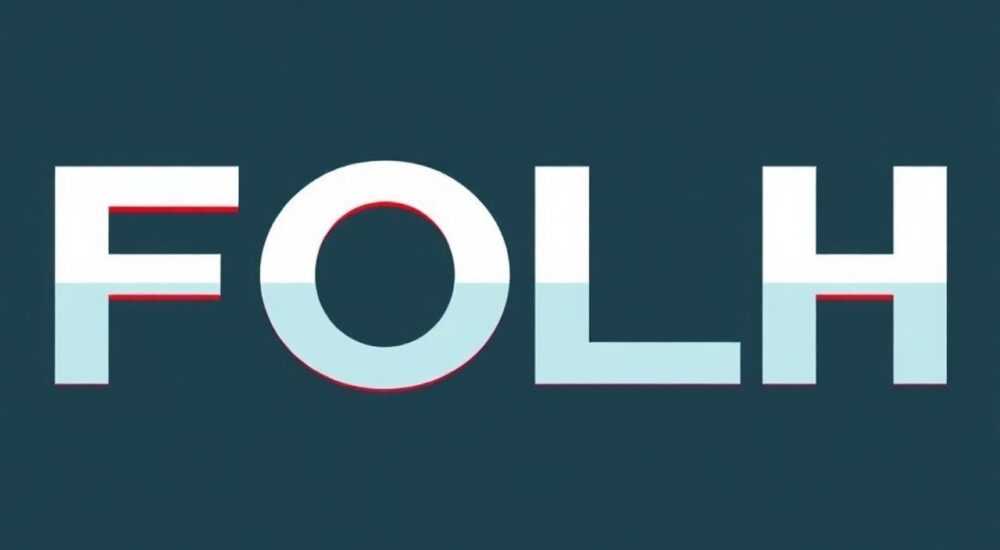
Как сделать толстый шрифт в фотошопе
В графическом дизайне толщина шрифта — один из ключевых инструментов визуальной иерархии. Она помогает выделить заголовки, усилить эмоциональное воздействие текста и сделать макет более читаемым. Однако не всегда в наличии есть нужный жирный начертание шрифта, особенно если используется кастомный или редкий гарнитур. В таких случаях дизайнеры часто сталкиваются с вопросом: как сделать толстый шрифт в Фотошопе? Ответ лежит не только в стандартных настройках стиля текста, но и в продвинутых методах обводки, масштабирования и векторного редактирования.
Почему важна толщина шрифта в дизайне
Толщина шрифта (или его «вес») — это характеристика, определяющая насыщенность линий символа. По международной классификации CSS она варьируется от 100 (тонкий) до 900 (черный). В дизайне вес шрифта влияет на восприятие информации: чем он выше, тем агрессивнее и доминантнее выглядит текст. Это делает жирные шрифты идеальными для заголовков, рекламных баннеров и call-to-action элементов.
Исследования Nielsen Norman Group показывают, что пользователи сканируют веб-страницы по F-образной модели. Жирные слова попадают в фокус внимания в 3.5 раза чаще, чем обычный текст. Это подтверждает важность правильного использования толщины шрифта для повышения конверсии и читаемости.
Однако не все шрифты имеют встроенное жирное начертание. Особенно это касается кастомных шрифтов, рукописных или декоративных гарнитур. В таких случаях дизайнер должен самостоятельно создать эффект утолщения, не нарушая пропорций и качества текста.
Как использовать встроенные жирные начертания
Перед тем как прибегать к хитростям, проверьте, доступно ли у вас настоящее жирное начертание выбранного шрифта. Большинство системных и коммерческих шрифтов включают несколько вариантов: Regular, Medium, Bold, Black.
Чтобы применить встроенное утолщение:
- Выделите текстовый слой в панели слоёв.
- Активируйте инструмент «Текст» (T).
- В верхней панели настроек найдите выпадающее меню «Стиль шрифта».
- Выберите вариант с пометкой «Bold», «Жирный» или числовым значением 700.
Если в списке нет жирного варианта, значит, шрифт не поддерживает его изначально. В этом случае можно установить дополнительные файлы начертаний (например, .otf или .ttf с суффиксом Bold), скачав их с официального сайта разработчика.
Ручное утолщение шрифта без жирного варианта
Когда встроенного жирного начертания нет, можно вручную увеличить толщину символов. Один из самых простых способов — масштабирование по горизонтали.
Шаги для ручного утолщения
- Выделите текстовый слой и нажмите Ctrl+T (или Cmd+T на Mac) для активации свободной трансформации.
- Удерживая Shift (для сохранения пропорций), потяните за боковые маркеры вправо и влево.
- Увеличьте ширину примерно на 10–20%. Слишком сильное растяжение исказит форму букв.
- Подтвердите изменения клавишей Enter.
Этот метод работает быстро, но имеет недостаток: буквы становятся не только толще, но и шире. Это может нарушить композицию, особенно в плотных блоках текста.
Методы утолщения через стили слоя
Более точный и профессиональный способ — использование стилей слоя. Он позволяет добавить толщину без деформации формы.
Обводка с внутренним выравниванием
- Щёлкните правой кнопкой по текстовому слою → «Стили слоя» → «Обводка».
- Установите положение «Внутри», размер — от 1 до 5 пикселей (зависит от размера шрифта).
- Цвет обводки выберите такой же, как у текста.
- Нажмите OK.
Обводка внутри имитирует увеличение толщины контура букв. Этот метод особенно эффективен для крупных заголовков.
Использование стиля «Стиль пера»
Photoshop CC 2021+ предлагает расширенные настройки стиля пера:
- Откройте «Стили слоя» → «Стиль пера».
- Выберите «Толщина» (Width).
- Увеличьте значение, чтобы утолстить контур.
- Настройте профиль, если нужно сгладить переход.
Обводка (внутри) |
Простота, обратимость, совместимость |
Может вызвать пикселизацию на маленьких шрифтах |
Стиль пера (толщина) |
Гибкость, векторная основа, высокое качество |
Доступно только в новых версиях Photoshop |
Масштабирование |
Быстро, не требует знаний стилей |
Искажает пропорции, не подходит для длинных текстов |
Увеличение толщины через редактирование контуров
Для максимального контроля можно преобразовать текст в контуры и вручную изменить толщину линий.
Пошаговая инструкция
- Щёлкните правой кнопкой по текстовому слою → «Создать контуры».
- Инструментом «Перо» (P) или «Прямой сегмент» выберите точки на контурах.
- Используйте команду «Выполнить обводку контура» с кистью большего диаметра.